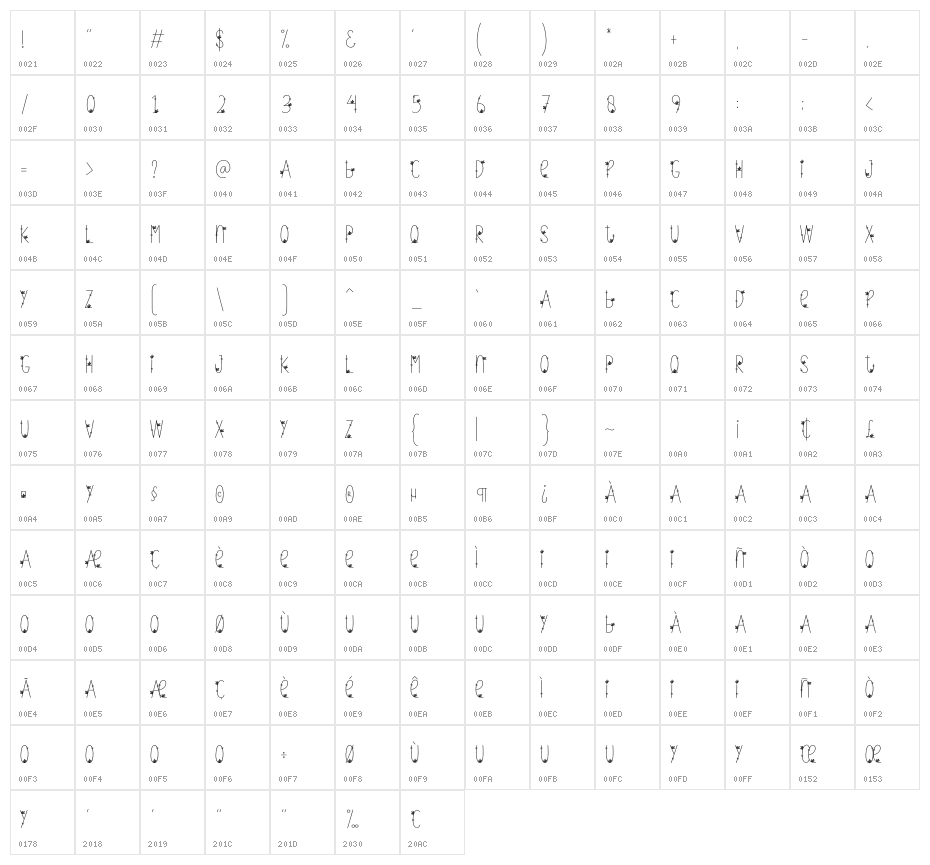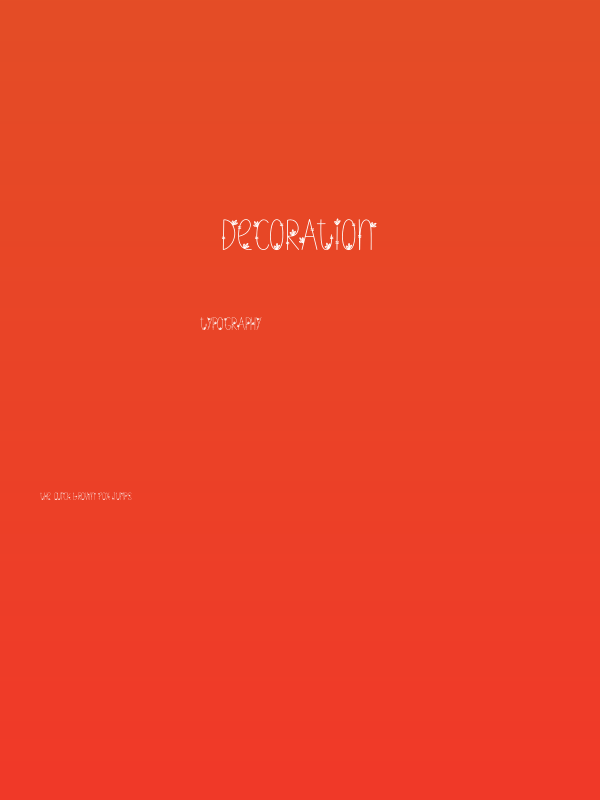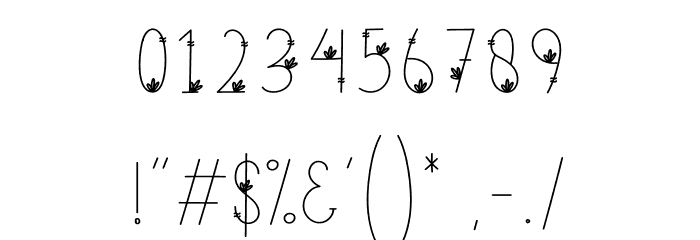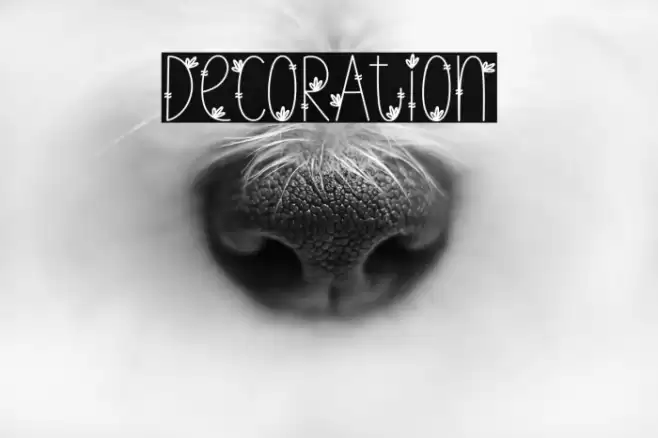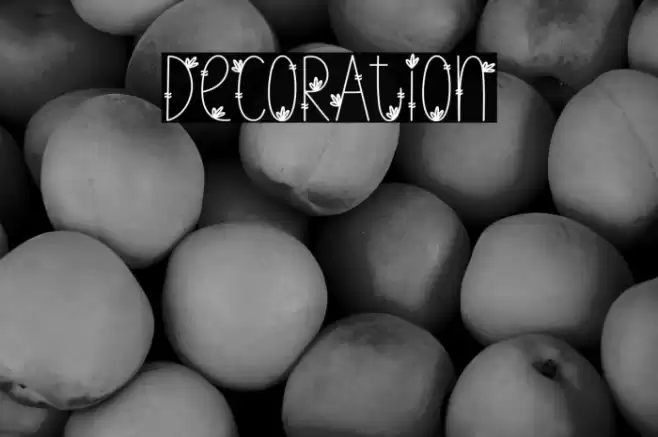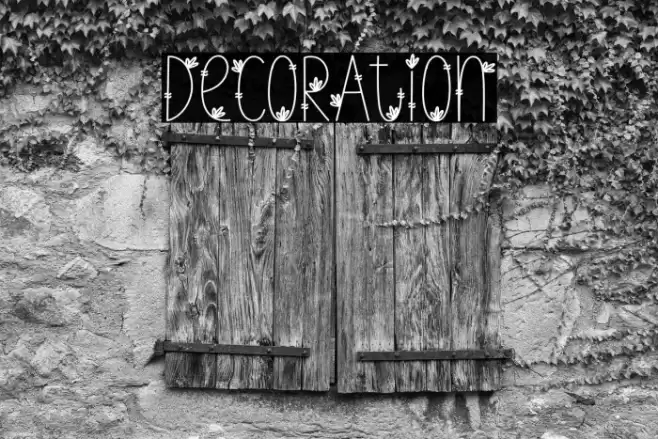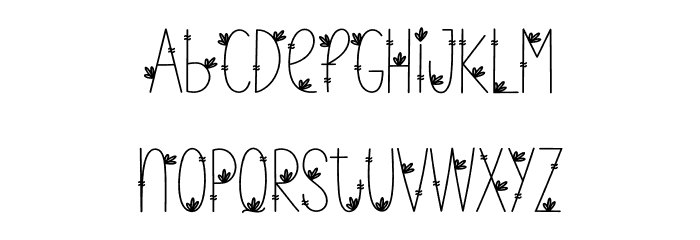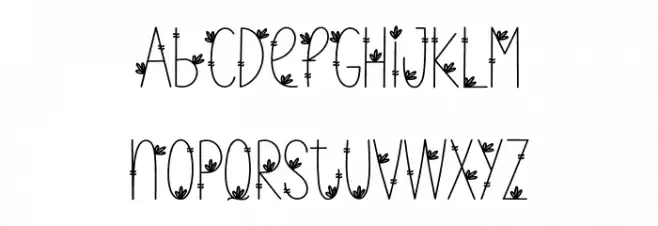
Decoration Font
| Caso d'uso | Logos, Headlines, Artistic projects |
| Progetti proposti | Ideal for eco-friendly branding, nature-themed invitations, children's book covers, and artistic posters. |